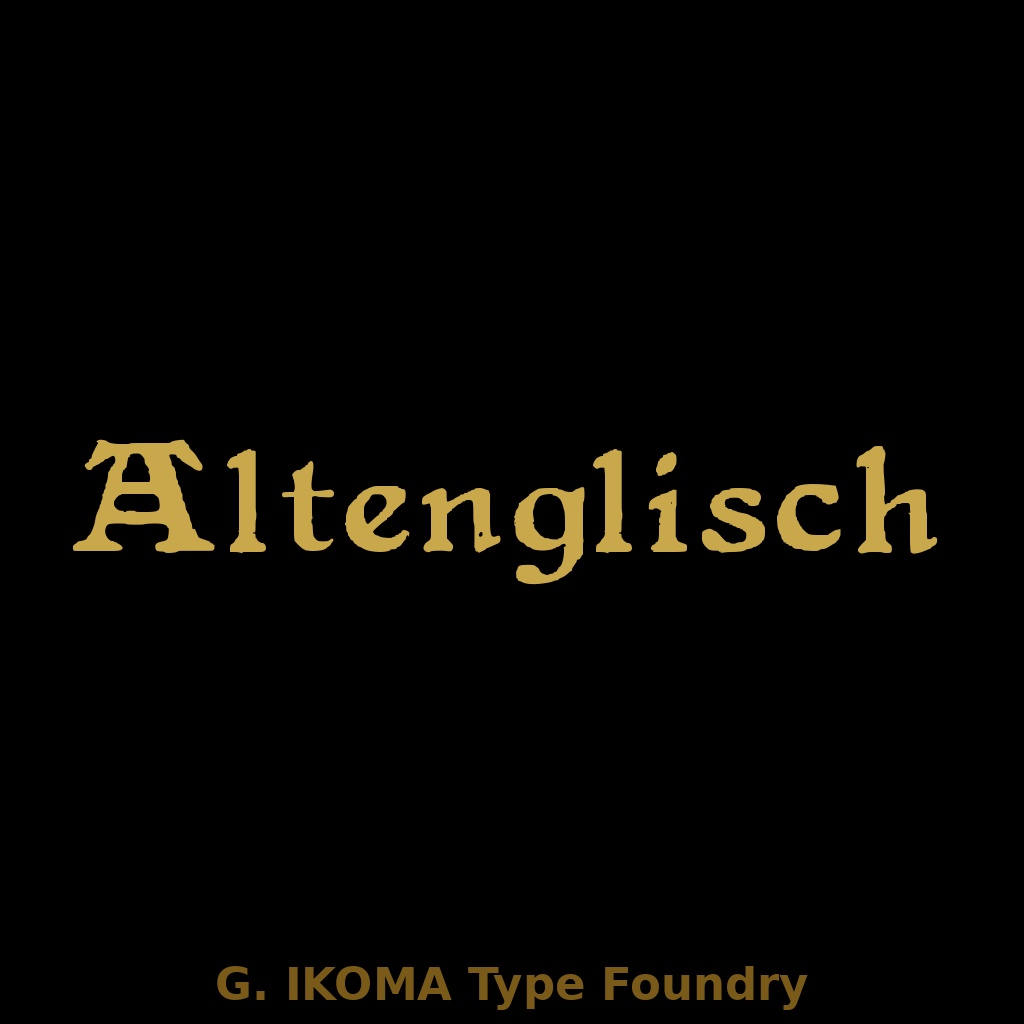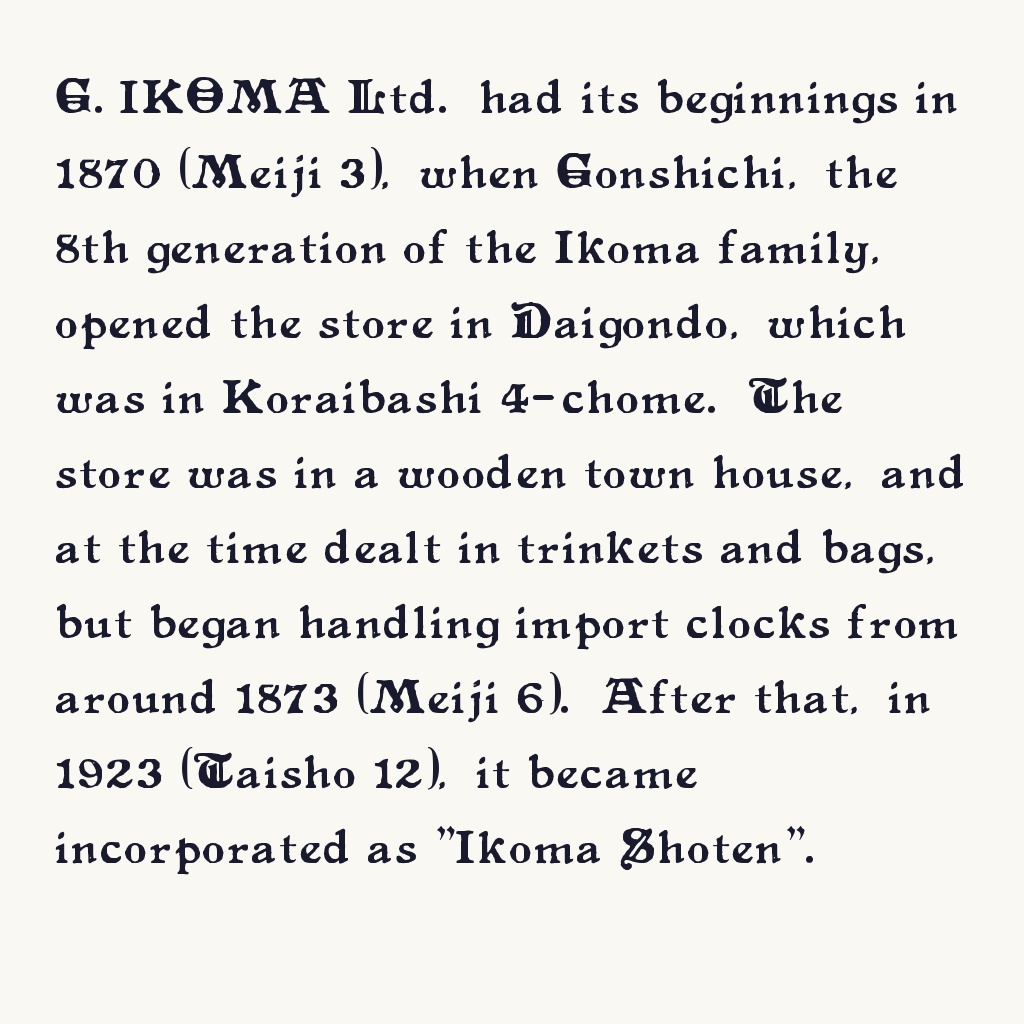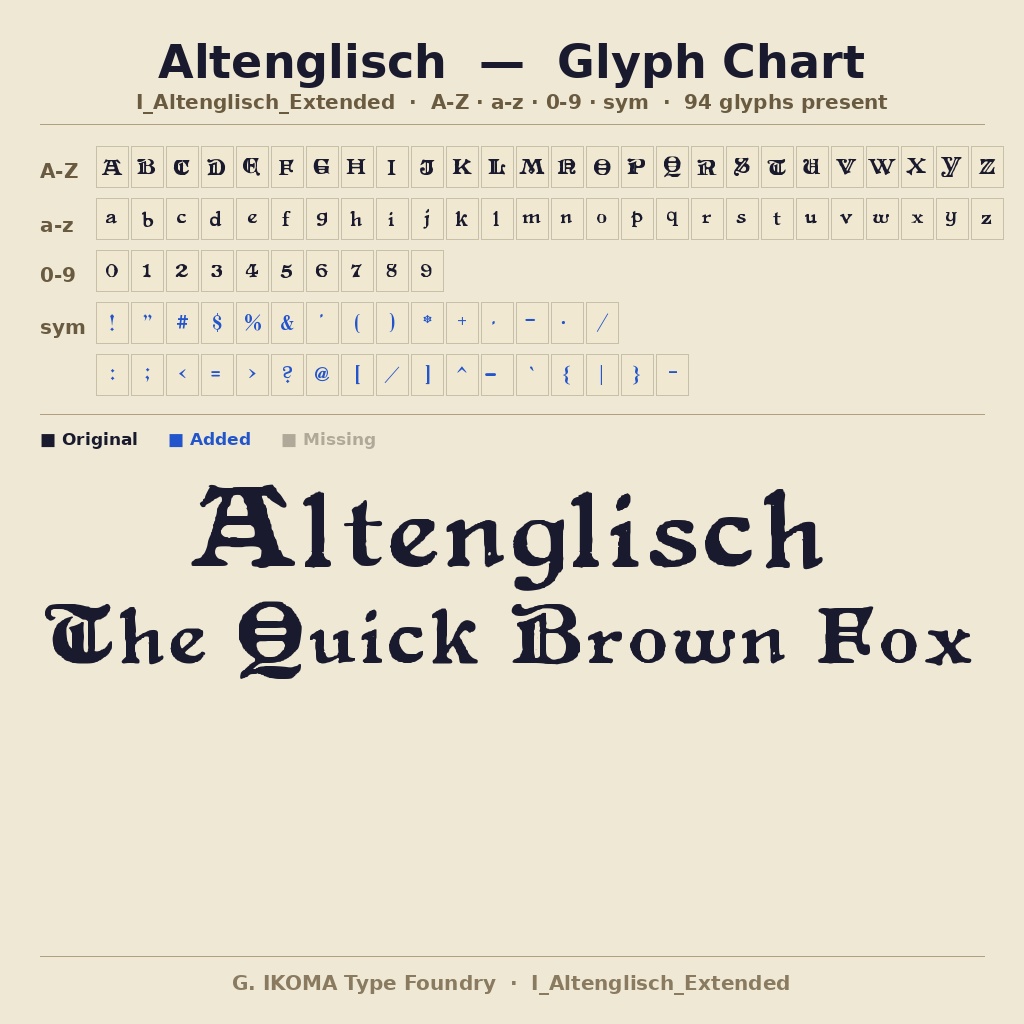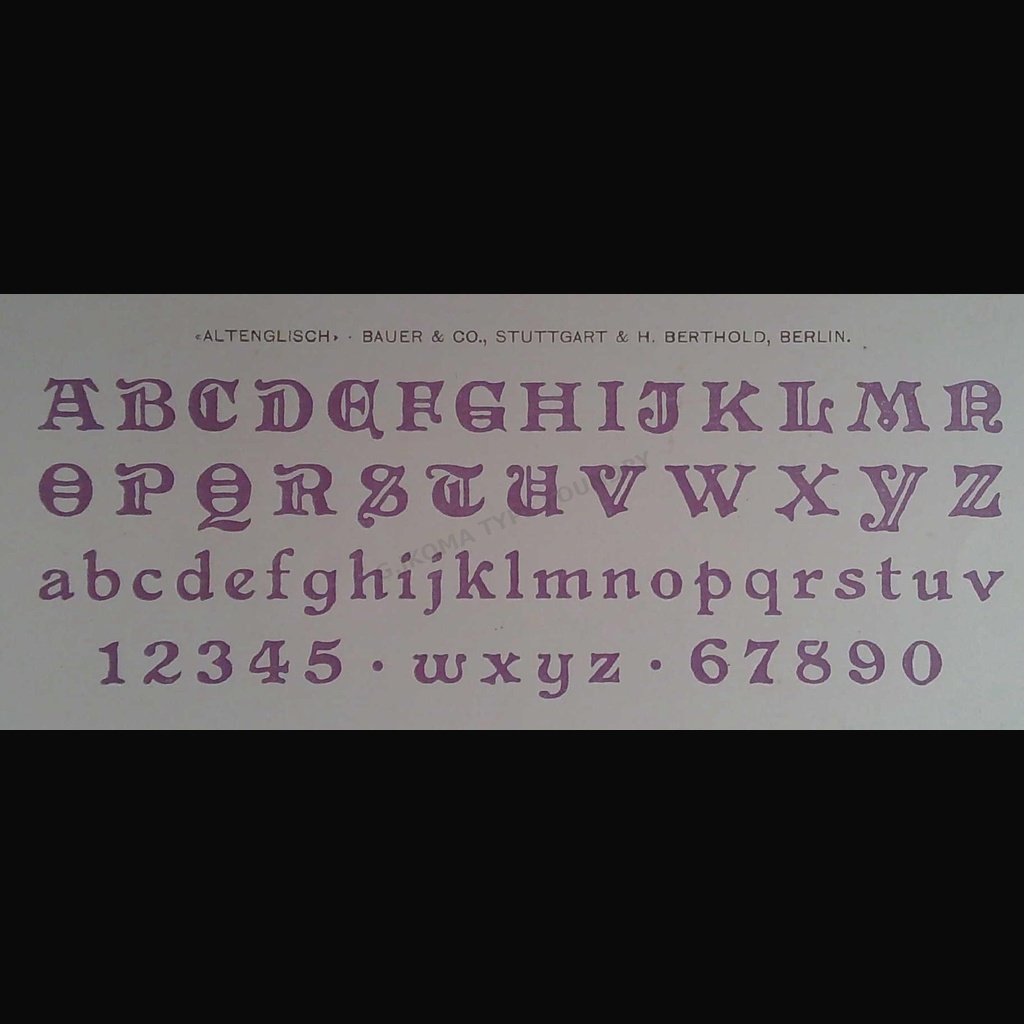
I Altenglisch — 欧文フォント / G. Ikoma Archives
━━━━━━━━━━━━━━━━━━━━━━━━━ 【フォントについて】 ━━━━━━━━━━━━━━━━━━━━━━━━━ Altenglisch Extended は、Old English(オールドイングリッシュ)様式をベースに G. IKOMA, LTD. がオリジナルデザインしたブラックレター系ディスプレイフォントです。 中世欧州の活字に由来するブラックレターの骨格を現代的な可読性で再解釈。 「Extended」の名が示す通り、横幅を広げたプロポーションが存在感あるタイトルやロゴに適しています。金属活字を思わせるインクトラップと力強いセリフが特徴です。 様式:Old English / Blackletter 収録グリフ:62文字(A–Z / a–z / 0–9) 欠落グリフ:なし 制作:株式会社生駒時計店 / G. IKOMA, LTD.(1870年創業) ━━━━━━━━━━━━━━━━━━━━━━━━━ 【ご購入前にご確認ください】 ━━━━━━━━━━━━━━━━━━━━━━━━━ 本書体はアルファベット大文字・小文字・数字(計62グリフ)のみの収録です。 記号・句読点・アクセント付き文字は含まれません。 Old English / Blackletter 様式の特性上、可読性よりも装飾性を優先した設計です。 ロゴ・見出し・タイトルなど大きく使う用途に向いていますが、 本文組版や小サイズでの長文には向きません。 ━━━━━━━━━━━━━━━━━━━━━━━━━ 【収録内容】 ━━━━━━━━━━━━━━━━━━━━━━━━━ ・I_Altenglisch_Extended.ttf ・LICENSE.txt(日英) ━━━━━━━━━━━━━━━━━━━━━━━━━ 【推奨用途】 ━━━━━━━━━━━━━━━━━━━━━━━━━ ・ロゴ・ブランド名 ・ゲームタイトル・ファンタジー系コンテンツ ・バンドロゴ・音楽系フライヤー ・ハロウィン・ゴシック系デザイン ・Tシャツ・グッズのプリントデザイン ・動画サムネイル・SNS投稿画像の見出し ・ポスター・チラシのタイトル 中世・ゴシック・ファンタジーの世界観を演出するデザインに最適です。 本文組版や小サイズでの常用には向きません。 ━━━━━━━━━━━━━━━━━━━━━━━━━ 【ライセンス】 ━━━━━━━━━━━━━━━━━━━━━━━━━ 本フォントは、個人利用・商用利用を問わず、印刷物、画像、ロゴ、バナー、 動画サムネイル等の制作に使用できます。 また、WebサイトやSNSで画像化された状態で使用することは可能です。 ただし、以下の行為は禁止します。 ・フォントファイルそのものの再配布、再販売、譲渡、共有 ・改変したフォントファイルの配布 ・本フォントを素材集、テンプレート、デジタル商品等に収録して再販売する行為 ・本フォントファイルをWebフォントとしてサーバーに設置・配信して利用する行為 ・アプリケーション、ゲーム、ソフトウェア、電子機器等への埋め込み利用 ・AI学習、機械学習、生成モデル訓練等への利用 ・本フォント自体または収録字形そのものについて独占的権利を主張する行為 詳細は同梱の LICENSE.txt をご確認ください。 ━━━━━━━━━━━━━━━━━━━━━━━━━ BOOTH: https://g-ikoma.booth.pm/